随着网络的迅速发展,人们对于字体的需求也不再仅仅局限于楷体、宋体、草书等经典字体,现在的很多新型字体也同样具有艺术性。当字体设计成为一种潮流,名字字体设计也开始流行起来,毕竟“字如其人”。现在很多明星也会找一些字体设计方面的专家为自己设计专属签名,那么大家也想拥有属于自己的名字字体设计吗?如果想要拥有的话,下面就跟着义启字库一起来看一看关于名字字体设计的具体内容吧!
为了满足人们对于名字字体设计的追求,网络上出现了一款名字字体设计生成器。这种字体生成器可以根据你的需求为你设计名字字体,甚至这些字体设计生成器中,还有专门适用于名字的字体类型,使用起来非常方便,可以满足大家的各种需求。
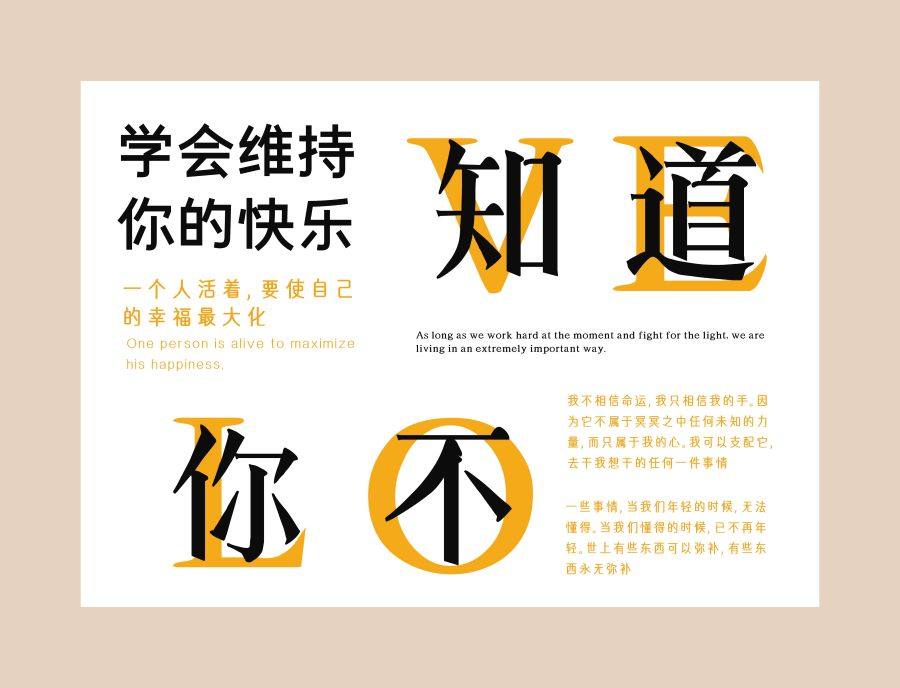
名字字体设计的方法有很多,可以根据自己的需求来设计自己名字的专属字体。如果是平常签字使用的话,可以使用字体设计中的叠加法,叠加法的适用范围是比较广的。不过,叠加法设计出来的名字字体是比较官方的,比较适合白领使用。
细节彰显品位,所以在设计名字字体时一定要注意细节的表现,或许一个笔画,就可以让别人看出你的自我修养与素质。如果不是很了解的话,也可以到义启字库搜索一下字体的类型。